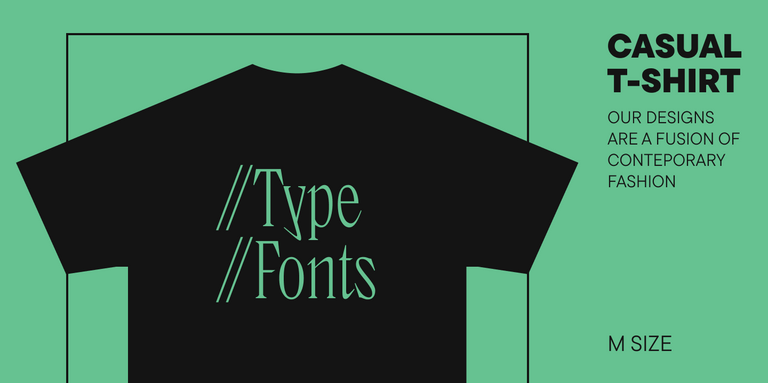
УниверситеТТ: Урок 4. Планирование шрифтового семейства
Мы продолжаем рассказывать о подноготной работы над шрифтами. Следующая тема плавно вытекает из предыдущих, поэтому советуем вам с ними ознакомиться, если вы еще этого не сделали. В статьях «Как не потеряться в работе над шрифтом. Искусство постановки задачи» и «Скетчи будущего шрифта: техника, оцифровка, оценка» мы рассказали о самых первых этапах шрифтового проекта.
В предыдущей статье речь шла о скетчах творческих. В этой мы тоже поговорим о скетчах, но уже более прагматичных — скетчах шрифтового семейства. Юлия Гонина, арт-директор TypeType и автор таких гарнитур, как TT Livret, TT Fellows, TT Autonomous и TT Ricordi Todi, объяснит, почему уже на начальных этапах проекта важно определиться с наполнением вашей гарнитуры.
Скетчи семейства и определение мастеров
После того, как вы определились с основной графикой шрифта и перешли с бумаги в вектор, самое время сделать скетчи для будущего семейства. Объясню, почему важно озаботиться этим сейчас, а не откладывать на потом.
Во-первых, нужно быть уверенным, что графические решения, которые вы примете в нормальном начертании, можно будет повторить во всех остальных стилях, даже в самых жирных и в самых тонких (или самых широких и самых узких, если они планируются). Это может накладывать на графику ограничения, которые нужно иметь в виду.
Во-вторых, с технической точки зрения необходимо определиться, с какими мастерами вы будете работать. Это позволит сэкономить много времени в будущем. Если вы работаете в современном шрифтовом редакторе, например, Glyphs или Fontlab 6 и выше, то вам не нужно отрисовывать абсолютно все начертания в семействе, достаточно нарисовать только опорные — так называемые мастера. Рассмотрим, что это значит, на примере наших шрифтов (гротеска и антиквы), брифы для которых мы составляли в прошлой статье.
В функциональной антикве мы, опираясь на предварительное исследование, решили остановиться на пяти толщинах. В теории нам достаточно нарисовать только крайние начертания — самое тонкое и самое жирное. Если количество точек в каждом знаке совпадает в обоих этих начертаниях, то программа сама сможет достроить любые промежуточные значения, то есть интерполировать их.
Это очень удобно и экономит кучу времени. Но как определить толщины всех начертаний? В случае с текстовыми шрифтами принципиально важно, каким по весу будет начертание Regular, так как оно является самым используемым, и именно его люди привыкли чаще всего видеть. Соответственно, есть некое общее представление о том, каким по толщине должно быть регулярное текстовое начертание, чтобы пользователю было комфортно с ним работать. Стоит вернуться к исследованию конкурентов, которое мы делали в прошлой статье, и подобрать толщину регулярного начертания так, чтобы оно сильно не выделялось из общей массы (если, конечно, у вас нет цели выделиться). Таким образом вы сможете определить толщины стемов «H» и «n» в вашем регулярном начертании. От этих значений вы будете впоследствии отталкиваться. Дальше можно таким же образом посмотреть толщины начертания Bold.
Оно тоже используется довольно часто, и есть смысл вписать его в общую массу шрифтов того же назначения. Хотя тут возможно больше отклонений от нормы. В итоге на этом этапе вам нужно получить два начертания по толщине, чтобы на их основе проработать все остальные стили семейства с помощью интерполяции и экстерполяции (автоматического построения начертаний, находящихся за пределами промежутка между мастерами).
Когда у вас появится больше двух начертаний, хорошей практикой будет равномерно распределить остальные толщины. Вы не захотите, чтобы у вас было, например, много похожих жирных начертаний и всего несколько тонких, которые сильно отличаются друг от друга. Если вы попробуете распределить толщины с одинаковым интервалом, получится именно такая ситуация. Для более плавного распределения толщин существуют специальные формулы. Найти значения по заданным параметрам можно с помощью этого сервиса. Мы в TypeType чаще всего используем формулу от Pablo Impallari.
В нашем случае есть предпочтительное значение Regular (в качестве конкретного числа обычно берется толщина стема «Н»), и значение Bold, в которое мы примерно хотим попасть. Теперь нам нужно поэкспериментировать со значениями и определить, во-первых, какие начертания у нас будут крайними (light – bold или regular – extrabold?) и по формуле подобрать значения промежуточных начертаний.
В итоге для функциональной антиквы получились следующие значения: Light (75*), Regular (92), Medium (114), DemiBold(137), Bold (160).
В данном случае указана толщина стема «H». Если у вас еще нет прописных знаков, можно указать, например, толщину стема «n».
Чем меньше у вас будет мастеров, тем быстрее будет идти работа над шрифтом. Но, с другой стороны, тем сложнее будет добиться адекватного вида промежуточных начертаний. Сейчас нужно понять, можете ли вы работать только на крайних мастерах (в нашем случае Light и Bold) или придется рисовать дополнительные промежуточные опорные начертания.Если вы еще не отрисовали тестовое слово в крайних начертаниях, то самое время это сделать. Теперь очень важно внимательно тестировать промежутки (так называемые инстансы — автоматически сгенерированные начертания), посмотреть их в тексте и в крупном размере, чтобы точно убедиться, что толщины, ширины, количество контраста вас устраивает в каждом начертании. Если брать нашу антикву, то она вполне может работать только на двух мастерах.